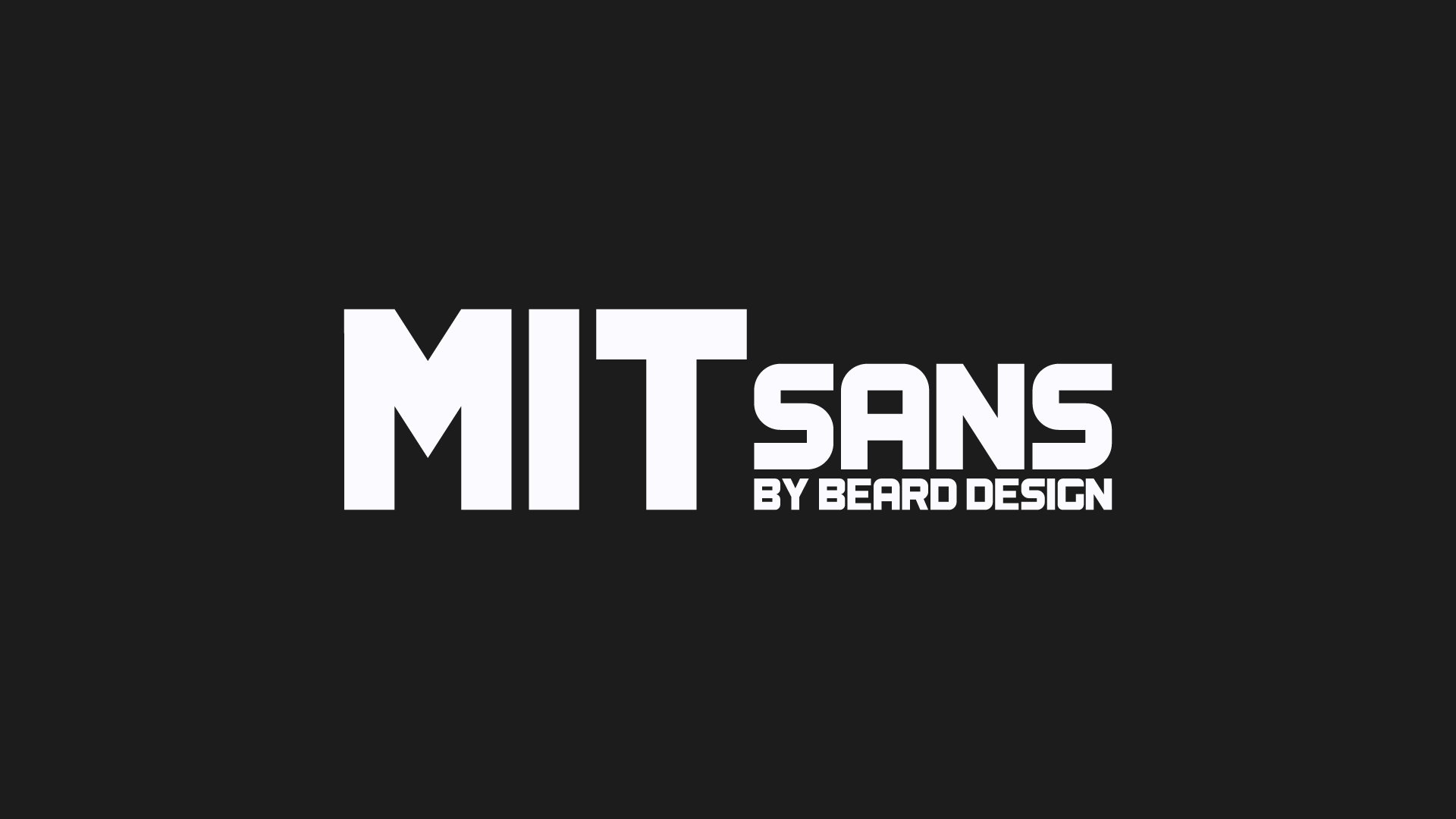
MIT Sans Font – Download Grátis
A fonte ‘MIT Sans Font’ é uma escolha perfeita para quem busca elegância e legibilidade no design editorial ou digital. Com traços simples e limpos, esta fonte sem serif proporciona um equilíbrio moderno que se destaca em qualquer layout. Seu designer, Beard Design, cuidadosamente criou este tipo de letra com uma aparência minimalista e funcional, ideal para textos em tela ou impressão. Sua simplicidade permite que ela atinja um alto nível de legibilidade mesmo em ambientes digitais mais saturados, tornando-a uma escolha atraente tanto para designers quanto para empresas buscando uma fonte clara e moderna. A ‘MIT Sans Font’ é uma ótima opção para quem busca estilizar o layout sem comprometer sua funcionalidade e simplicidade.
Designer: Beard Design